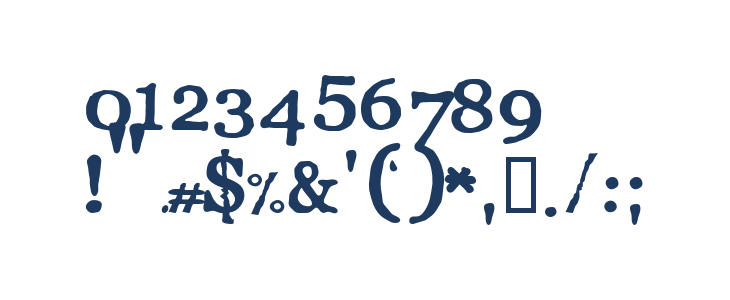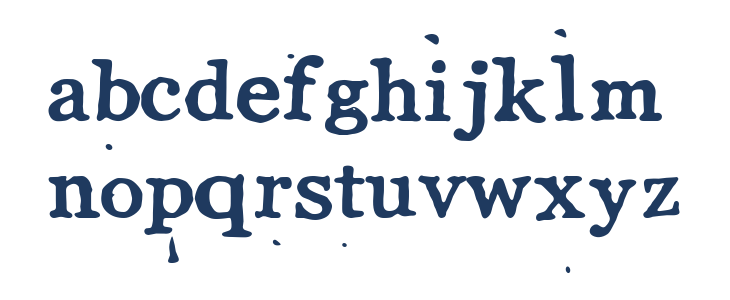
✎ Distorted Eroded
| Projets proposés | Ideal for projects that require a vintage or handcrafted aesthetic, such as posters, branding for artisanal products, book covers, and retro-themed designs. |